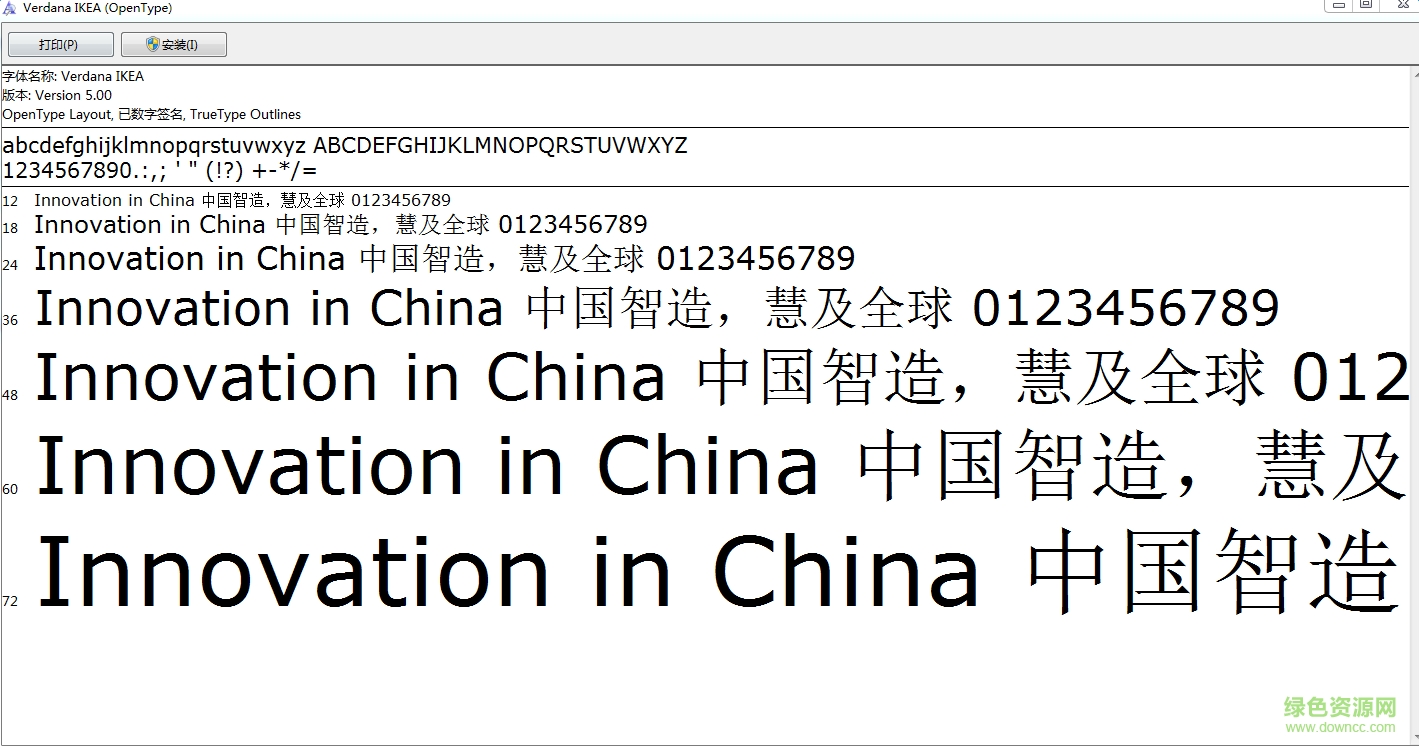
verdanaikea字體是一款大方工整的英文非襯線體,該字體結構嚴謹,布白得當,看起來非常規(guī)范,產(chǎn)品包裝、海報宣傳等領域都可使用,歡迎下載!
1.早期的無襯線字體設計,--如Grotesque或 Royal Gothic體
2.新grotesque或稱為過渡體--目前所謂的標準無襯線字體,如helvetica(瑞士體), Arial和Univers體等
3.古典體或稱為人文主義體--(Johnston、Frutiger、Gill Sans、Lucida、Myriad、Optima、Segoe UI、Tahoma、Trebuchet MS、Verdana)。這些字體是無襯線字體中最具書法特色的,有更強烈的筆畫粗細變化和可讀性。
4.幾何體--(Avant Garde、Century Gothic、Futura、Gotham)。顧名思義,幾何無襯線體是基于幾何形狀的,透過鮮明的直線和圓弧的對比來表達幾何圖形美感的一種無襯線字體。